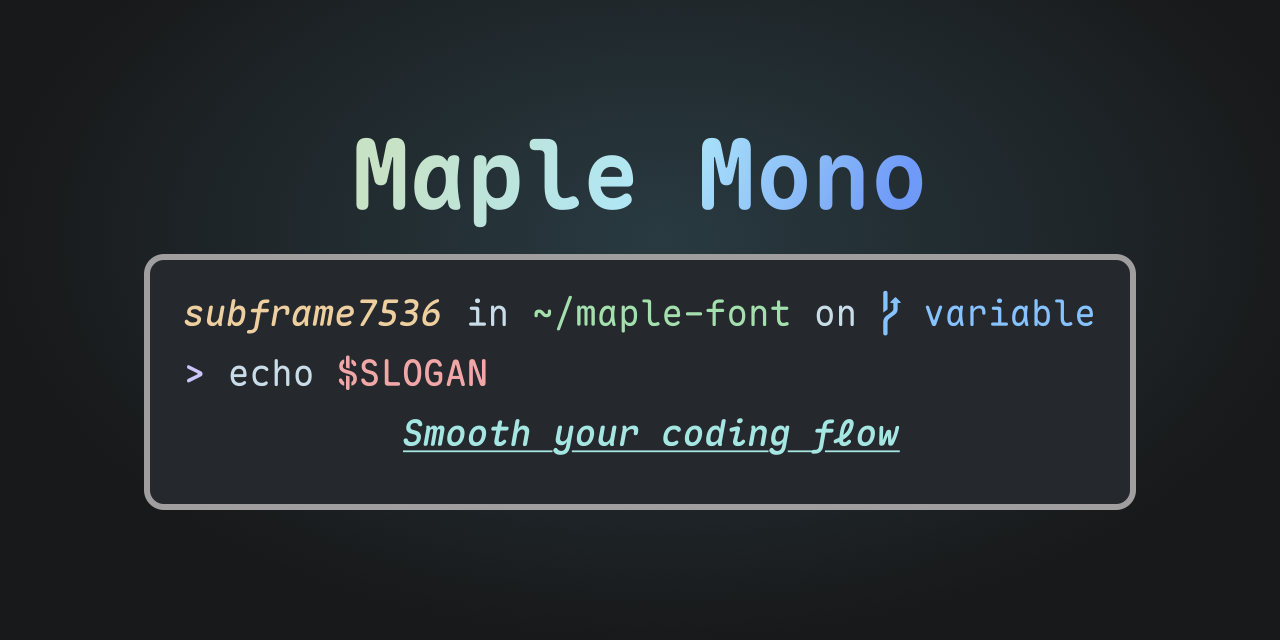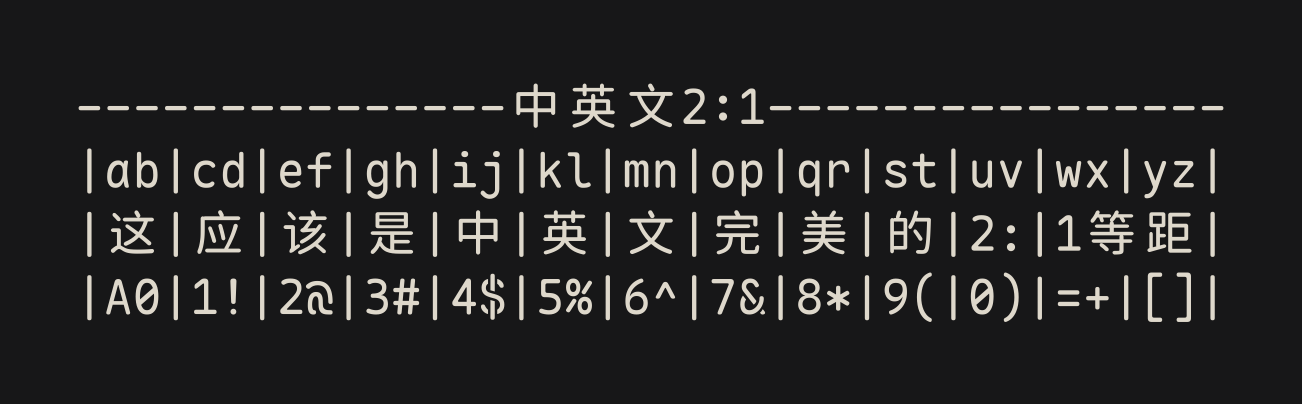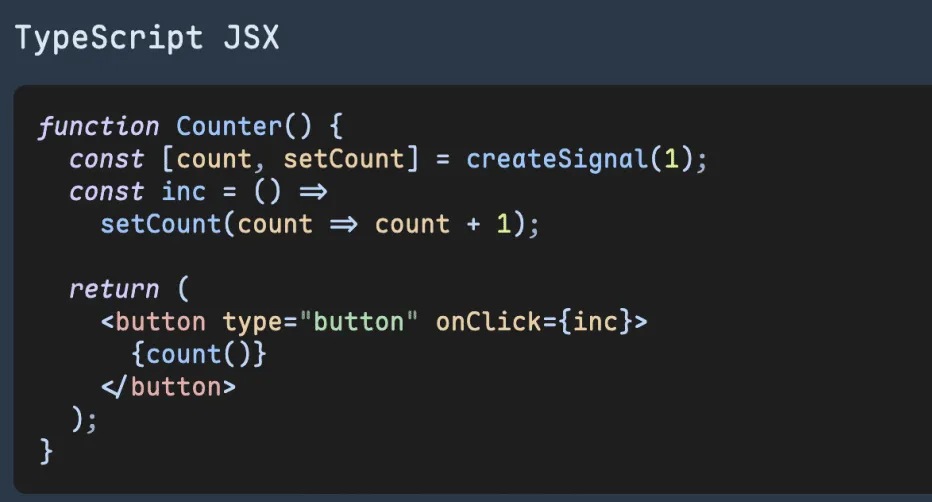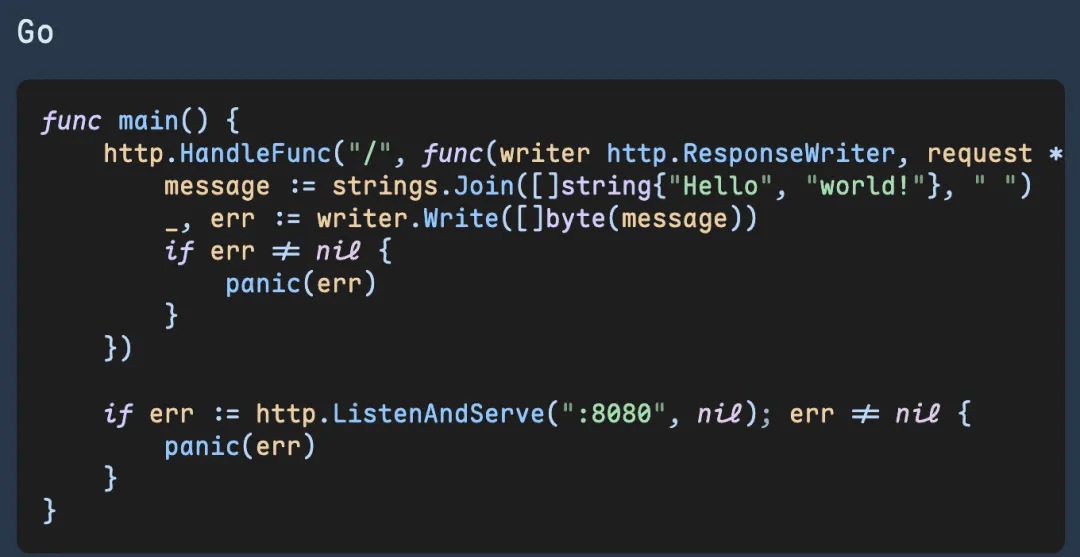
开源字体Maple Mono
特性
可变 - 无限的字体粗细,以及手工微调的斜体字形。
丝滑 - 圆角,独特的 @ $ % & Q -> 字形,以及手写风格的斜体 f i j k l x y。
实用 - 大量的智能连字,详见 features/。
图标 - 提供 Nerd-Font 嵌入的版本,添加图标支持。
定制 - 自由开关或者构建 OpenType 字体特性,打造您专属的字体。
换言之:
可变字体:无限的字体粗细,以及手工微调的斜体字形
丝滑体验:圆角设计,独特的 @ $ % & Q 字形,及手写风格斜体 f i j k l x y
实用性强:大量的智能连字支持,特别适合代码显示
图标支持:提供 Nerd-Font 嵌入的版本,添加对终端图标的支持
高度定制:自由开关或者构建 OpenType 字体特性,打造专属字体
很少有等宽字体设计有圆角
很少有等宽字体对 Nerd-Font 和中文优先支持。
等宽代码字体实现了完美的中英文宽度 2:1 显示,非常让人舒适。其实现了中英文 2:1 宽度完美对齐,也就是说一个中文字符的宽度正好等于两个英文字符的宽度。这款字体不仅在设计上独具匠心,作者深知程序员在写代码时对字体的苛刻需求,还针对编码场景做了大量优化,让代码的阅读变得更加愉悦。Maple Mono 中文等宽字体支持 Windows、macOS、Linux 三大操作系统, 以及 VS Code、JetBrains 全系列 IDE、Visual Studio、XCode、Android Studio、Cursor 等主流代码编辑器。同时此字体还有连字版和不连字版本可选,对高分辨率屏幕的渲染也有支持,兼容性完全不用担心。
手写圆角风格!告别 “棱角分明” 的刻板印象
传统的等宽字体,为了追求字形的规整,往往显得比较生硬,棱角分明,长时间看下来容易视觉疲劳。 Maple Mono 则巧妙地采用了圆角设计,让字体整体看起来更加柔和、丝滑,减少了视觉上的冲击感,即使长时间盯着屏幕 coding,眼睛也不容易感到疲劳。
手写斜体, 让你的代码更具个性
斜体字在代码中经常用于注释或者强调, 但很多等宽字体的斜体都是通过程序自动生成的, 角度僵硬, 效果往往不尽如人意。 Maple Mono 则不一样,它的斜体字形是 手工微调 的, 甚至 f i j k l x y 这些字母还采用了 手写风格 的斜体设计, 看起来更加自然、流畅, 充满了个性, 让你的代码瞬间提升一个 level!
智能连字特性, 代码可读性更佳
连字 (Ligatures) 是现代编程字体的一大趋势, 它可以将多个常用的编程符号组合成一个更美观、更易读的整体。Maple Mono 在这方面可谓是下足了功夫, 提供了 大量智能连字, 像 =>, &&, ||, .., ..., /*, /** 等等符号, 都做了精心的连字优化显示。针对一些程序员经常用的注释用语,比如 [TODO]、[DEBUG]、[ERROR] 等特殊的字符串,它还能转换成更加显眼的标签样式来显示,看代码注释时可以更加显眼,非常贴心。
Nerd Font 支持,在命令行终端上能显示图标
如果经常在命令行终端或者 PowerShell 中工作, 那么 Maple Mono 字体对 Nerd Font 支持绝对是一个加分项!Maple Mono 提供了 Nerd-Font 嵌入版本。内置了 PowerShell、Linux 终端等常用图标,让你的命令行界面也能拥有漂亮的图标显示,阅读体验更上一层楼!
可变字体!无级调整字体粗细,自由定制你的专属字体
V7 版本 还引入了 可变字体 (Variable Font) 技术,你可以 无限调整字体的粗细,找到最适合自己的字重。而且 Maple Mono 还提供了 丰富的自定义选项,可以自由开关 OpenType 字体特性,甚至可以定制构建属于你自己的专属字体!这个自由度简直太高了!具体的定制方法可以参考官方文档或者在线尝试。
开发者称于2025年3月中旬发布的 V7 是一个完全重制版本,提供了可变字体格式和字体工程源文件,重新设计了超过一半的字形,并提供更智能的连字。